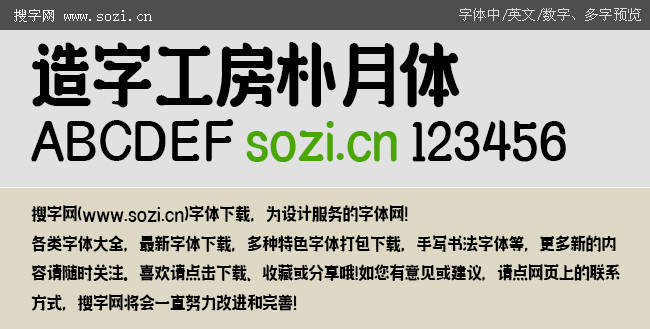
造字工房樸月體
搜字網(wǎng)給大家提供一款造字工房樸月體中文字體下載,造字工房樸月體端秀清新,筆畫方圓兼?zhèn)洌舒展,橫畫首尾呼應(yīng),溫潤(rùn)秀美,整體風(fēng)格不燥不潤(rùn)、張弛有度,有極強(qiáng)的視覺表現(xiàn)力。此款字體適用于海報(bào)設(shè)計(jì)、報(bào)刊雜志標(biāo)題、書籍封面設(shè)計(jì)等應(yīng)用。(本字體為個(gè)人非商用版,如需要商用請(qǐng)聯(lián)系官方購(gòu)買版權(quán))